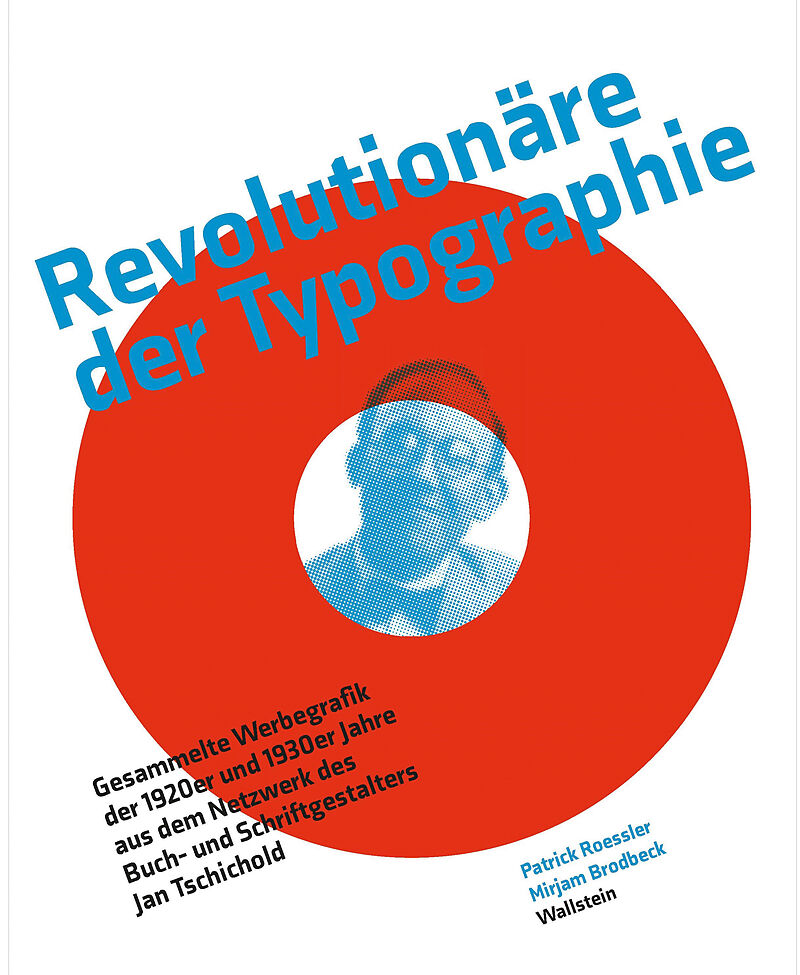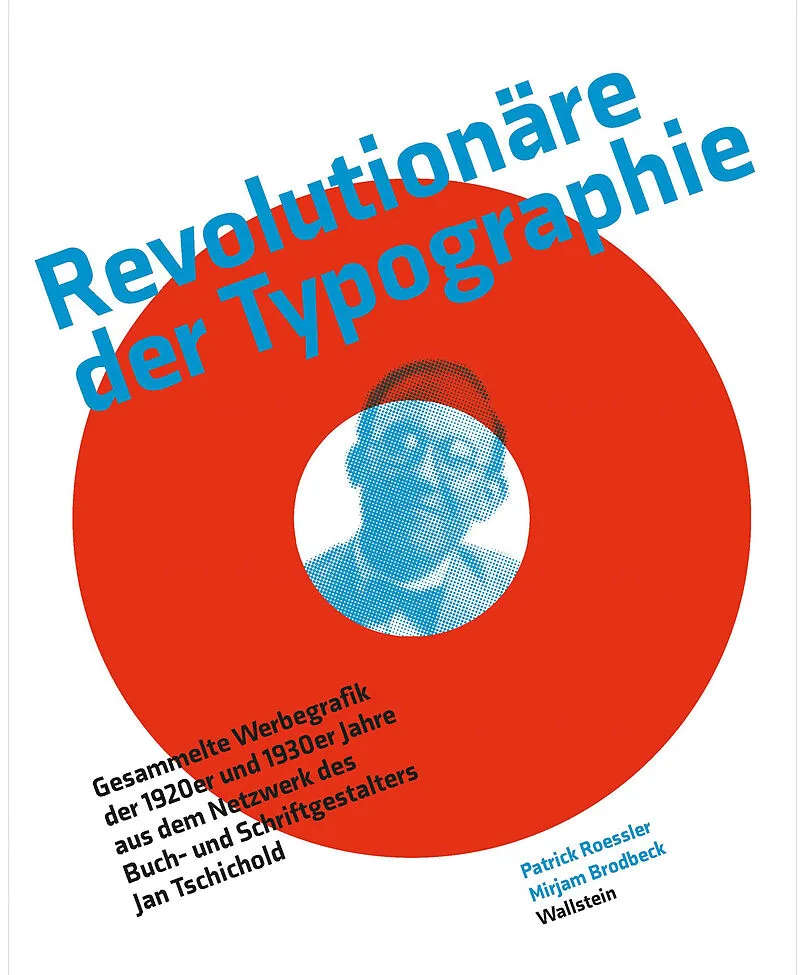
Revolutionäre der Typographie
Weltklasse-Grafikdesign aus den bis heute stilprägenden 1920er und 1930er Jahren: die Sammlung Jan Tschichold der Schule fur Gestaltung Basel. Innerhalb eines europäischen Netzwerks der Avantgarde zusammengetragen, enthält die »Vorbilder-Sammlung« des deutsch-...